「色部義昭:WALL」展のギャラリートークから・その2
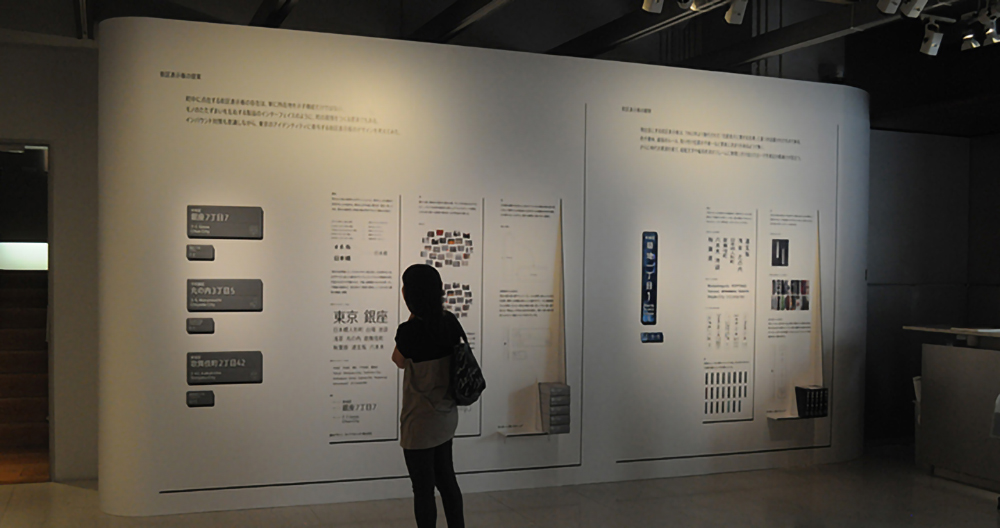
シビックプライドが都市を変えていく
「色部義昭:WALL」展(2015年9月2日から28日までギンザ・グラフィック・ギャラリーで開催)のギャラリートーク第2弾「世界のシビックプライドについて」には、色部義昭氏(日本デザインセンター、グラフィックデザイナー)、紫牟田伸子氏(編集家、プロジェクトエディター、デザインプロデューサー)と鈴木功が出演。最初に紫牟田氏がシビックプライドの考え方と世界の事例を、続いて鈴木が都市フォントを紹介し、色部氏へとつなぐという構成でした。そこから、いくつかの発言をピックアップしてご紹介します。
色部:以前、同じ職場の先輩だった紫牟田さんから渡されて読んだ本を通じてシビックプライドという考え方に触れました。この本がすごくおもしろくて、日本では都市のデザインが議論される機会が少ないなか、自分がグラフィックデザイナーとして、いつかそういうことに携わりたいなと考えるようになりました。今回ギャラリーの1階で展示している街区表示板のプロジェクトは、僕なりにシビックプライドを意識して行ったものです。
紫牟田:2005年くらいにシビックプライド研究会を始めました。そして、シビックプライドって何だろう、世界で何が起きているんだろうというのを調べてまとめたのが、2008年に出版した本です。シビックプライドという言葉を日本語に直そうとすると、あまりうまくいかなくて、たとえば「郷土愛」と訳してしまうと、ちょっと違う。都会には、働きにくる人も、遊びにくる人もいて、それで街がおもしろくなっているわけです。だからシビックプライドというのは、そこで生まれ育った人だけのものではなく、「この街に関わっている」という当事者の思いなんじゃないか。それが、そのときに考えたことなんですね。
デイヴィッド・ミリバンドというイギリスの政治家によると、現代では人やコトが都市を象徴するものとなってきていて、都市を活性化するためには人の心を活性化しなければならない。だから都市の再生には、人の心に生まれ育まれるシビックプライドがとても大事だということを言うんですね。今回の色部さんの提案は、標識、そして文字という根幹の問題で、それが少し変わるだけで街の構造も変わってしまうという発見があって興味深かったです。指示標識は、都市構造そのものの提示だと思うんです。街区表示板が清々しさをもってデザインされていることが、都市のあり方へと人の意識を向けていくきっかけになるかもしれません。
鈴木:紫牟田さんの監修されたシビックプライドの本には大きな影響を受けていて、まだ都市フォントのアイデアがふわふわしていた時期に、この本に出会ってプロジェクトの骨格を固めることができました。新刊の「シビックプライド2」には、僕も執筆者のひとりとして都市フォントの事例について紹介しています。
都市フォントのひとつである濱明朝は、横浜開港150周年に当たる2009年から取り組んでいるプロジェクトです。この書体は、みなとみらいから見た横浜の景色から生み出されました。横画に横浜を象徴する氷川丸のフォルムを取り入れているほか、細部には風にはためく旗のイメージなどを盛り込み、港らしさを演出しています。また、明朝体のイメージは、横浜開港に続く文明開化において大きな役割を果たした金属活字とも重なります。
金シャチフォントは、僕の生まれ故郷である名古屋のプロジェクトです。ディティールには、金シャチのピチピチしたかんじというか、硬直化しがちな明朝体に動きを取り戻すような感覚を取り入れて作っています。キーワードで言えば、デコラティブ、ゴージャス、反り、巻き。それを名古屋のアイデンティティだと言ったら怒られるかもしれませんが、「ちょっとやりすぎてしまう」気質を書体で表現できたらおもしろいのではないかと考えています。
今回の街区表示板のための東京シティフォントでは、江戸から現代の東京へと受け継がれている人々の気質・好みを書体の属性へと置き換えることで、結果として金シャチフォントとは対照的なテイストとなりました。飾りのないサンセリフ、ウエイトは軽め、プロポーションはやや縦長でほっそりしたイメージ、そこに筆で書いたような抑揚を入れて勢いを加味しています。
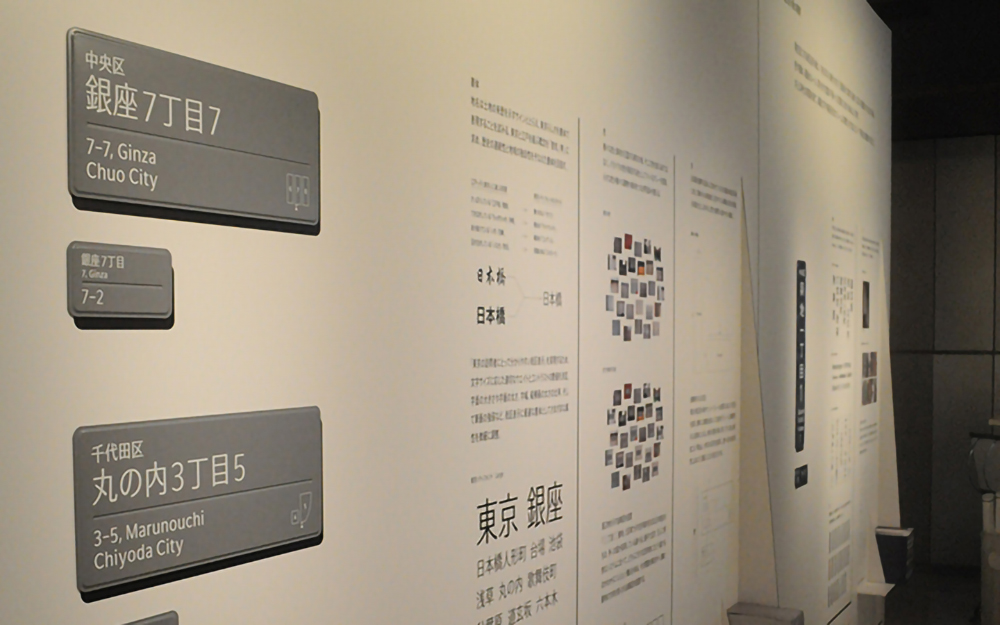
色部:サインには、案内機能の向上、街歩きの推進といった働きがあります。加えて、たとえば家でもどこでも、散らかっているとその場に対する関わり方が雑になっていくと思うのですが、きれいに整えると、ていねいな気持ちで接するようになる。サインには、そういう働きがあると思っています。最小点、小さなポイントでも、変えることによって、まわりのものや空間が愛でられるようなシーンができていくのではないでしょうか。
海外の例を見ると、ロンドンのサインシステムは、書体に特徴があります。地下鉄用に作られたジョンストンという書体が、次第に市民権を得て、ロンドンらしさを醸成するひとつのアイテムにまで成長しています。ロンドンでは2012年にオリンピックがあり、その前に「Legible London」というスローガンのもとで公共サインの整備を行いましたが、ここでも同じ書体が使われています。僕は最初、このサインシステムは観光客のために作られたのだと思っていたのですが、実は「市民が歩くことで健康になる」というテーマがあったことを最近知りました。実際に歩くことが促進されれば、通り沿いの商店に目がいくことになり、経済効果も期待できる。デザイン的にもすばらしいですし、参考になる事例だと思います。
ひとつの新しい書体の歩みは、最初はひとりのデザイナーがそれを採用するってことで始まるかもしれませんが、さまざまなメディアに展開されることで、すごい勢いで浸透していくイメージがあります。都市のデザイン的なイメージを作り上げていくためには、書体を作るのが一番近道でコストがかからない。それも、今回のプロジェクトを通して発見したことのひとつです。